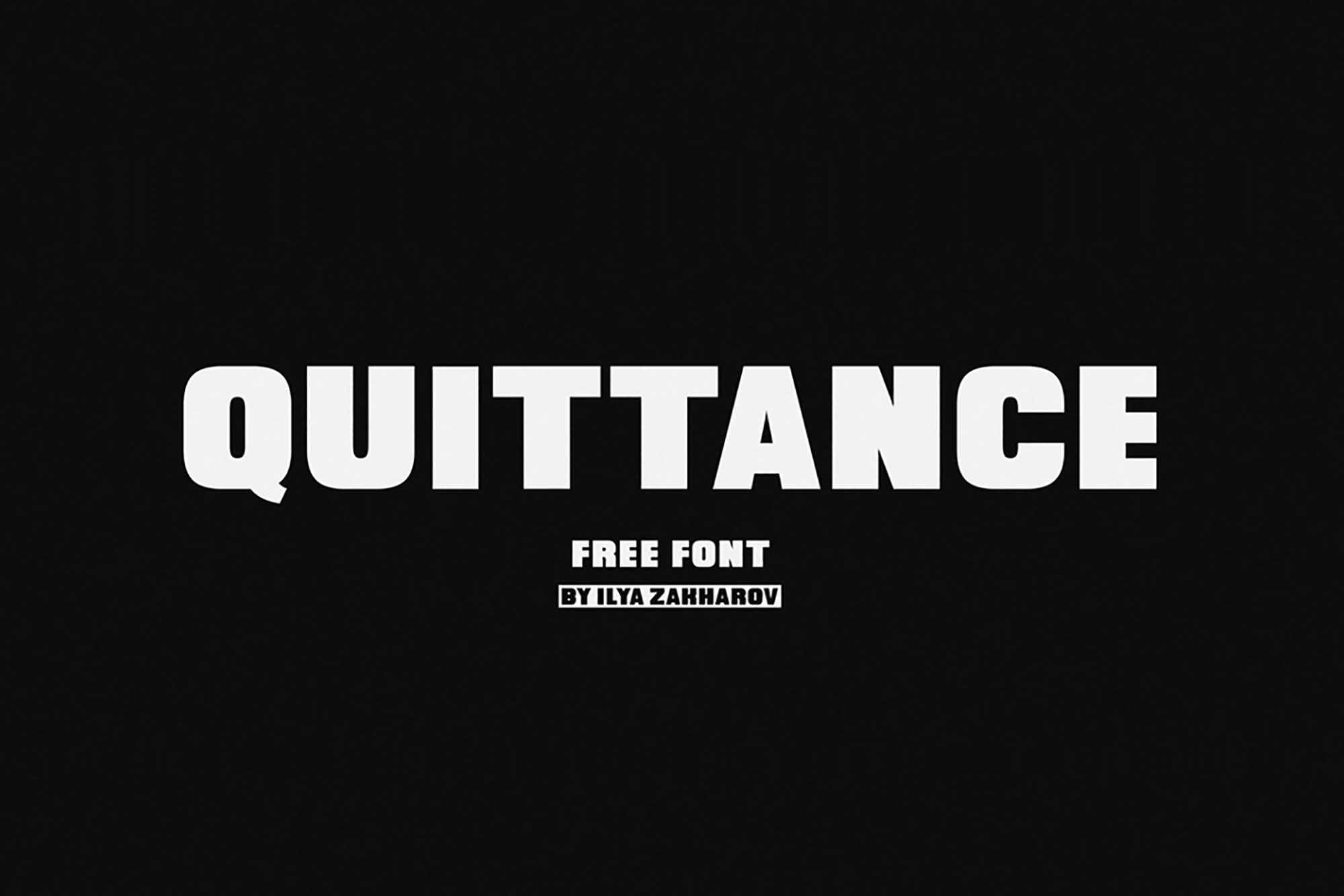
Quittance Sans Serif Font – Download Grátis
Modernas marcas têm menos tempo para se conectar com seus públicos e, na tentativa, querem comunicar suas mensagens como mais atraentes, acessíveis e digestíveis. Diante de um flood de mensagens publicitárias, as pessoas selecionam aquilo que acham atraente e ignoram marcas que não se envolvem pessoalmente na mensagem. É claro por que os ideais modernistas de simplicidade e eficiência permanecem válidos e que os sans serif são cada vez mais comuns. Esse recurso de fonte sans serif, Quittance Sans Serif, foi projetado para combinar perfeitamente com o design moderno e clean das marcas contemporâneas. Suas linhas retas e claramente legíveis são ideais para criar uma conexão forte e imediata. Seus traços finos e elegantes dão um toque sofisticado aos seus designs. Este recurso está equipado para moldar o visual de suas mensagens de um modo que seja irresistivelmente atraente e fácil de entender, adequado para a era moderna de marketing onde a atenção é rara e o tempo curto.